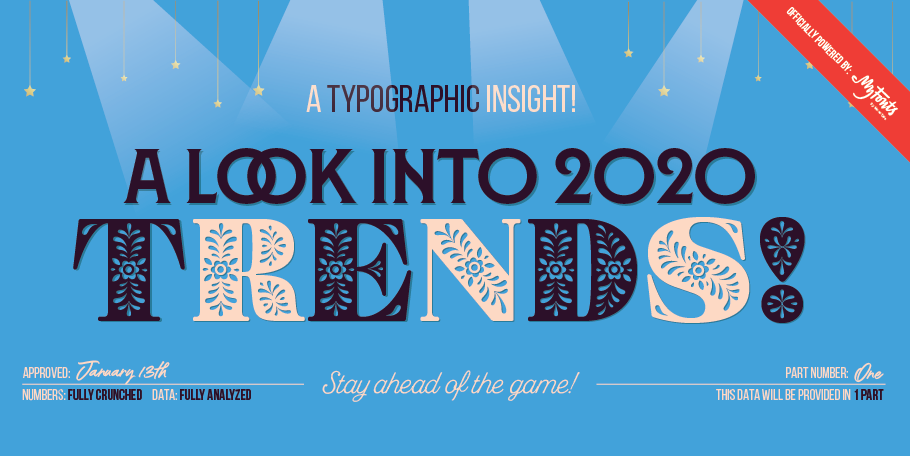
2020 Police Tendances pour les designers à utiliser cette année
" Des polices douces et des visages amicaux invitent les lecteurs à découvrir les annonces, les publications, les pages web et les jeux. "
L'utilisation de polices de caractères classiques dans vos projets présente peu de risques. Vous ne pouvez pas vous tromper avec Frutiger Suivante, Garamond ou Brandon Grotesque. Ces polices de caractères classiques sont comme une robe noire basique ou un blazer bleu marine.
Mais qu'en est-il si votre projet nécessite une typographie de dernière minute ? Que se passe-t-il si vous voulez une police qui s'inscrit dans une tendance typographique en plein essor - une police qui garantira que vos créations graphiques ou interactives sont fraîches, élégantes et branchées ? Lire la suite.
Même s'il semble que des centaines de nouvelles polices de caractères sortent chaque jour, les nouveaux designs police les plus en vogue se classent dans les catégories suivantes cinq catégories pour 2020:
• Sans géométrique
• Barres obliques et caractères alternatifs
• Polices et des visages amicaux
• Incrustée, gravée et délicieuse
• Square Sans
" Les swashs et les caractères alternatifs sont des éléments de personnalisation, tandis que les motifs incrustés, gravés et texturés se distinguent dans la foule ! "
Police Tendance n° 1 : Sans géométrique
Les polices géométriques sans fioritures sont à la mode depuis un certain temps, et ce pour de bonnes raisons. Elles s'expriment avec clarté et autorité. Beaucoup bénéficient également d'une large gamme de graisses et de proportions, ce qui les rend idéales pour tout ce qui concerne les mots-symboles, les marques, les titres et la signalétique. Le minimalisme est personnifié dans des designs tels que Gilroy, Biennale et Codec Pro. D'autres, comme Campton, sont adoucis par une subtile influence calligraphique. Cette influence calligraphique est encore plus forte dans des designs comme Noah et Proxima Nova.
Grâce à leurs grandes hauteurs de x, à leurs compteurs ouverts et à leurs formes de caractères simples, ces caractères permettent aux entreprises et aux produits d'exprimer leur marque de manière transparente partout où un public peut s'y intéresser, notamment sur les sites Web, dans les publicités, dans les messages d'entreprise, sur les emballages - et bien plus encore. Choisissez l'un de ces modèles et vous ajouterez à votre boîte à outils une police de caractères puissante, tendance et certainement classique.
• Biennale de Latinotype
• Campton de Rene Bieder
• Codec Pro de Zetafonts
• Gilroy de Radomir Tinkov
• Noah de Fontfabric
• Proxima Nova de Mark Simonson
Police Tendance n° 2 : les traits d'union et les caractères alternatifs
Les swashes et les caractères alternatifs sont synonymes de personnalisation et d'adaptation. Ils permettent de créer des titres et des bannières uniques et sont également parfaits pour les liens de navigation, les sous-titres et les emballages. Ce sont des choix idéaux pour les occasions spéciales qui exigent plus que des mots sur du papier. Certaines, comme Aire et Artis Sans, sont sophistiquées, avec des touches sensuelles et des fioritures. Le Desire a la proéminence d'une police à empattement classique et est rempli d'alternances, de ligatures, de swashs et même de mots d'accroche ! Gelato Fresco est aussi accueillant qu'une lettre à la main, tandis que VVDS Organum est un Didone majestueux à sept graisses avec une attitude enjouée. Ses nombreuses ligatures discrétionnaires et ses alternatives stylistiques permettent de créer facilement une typographie sur mesure.
• Aire de Lián Types
• Artis Sans de Wiescher Design
• Désir de Borges Lettering
• Gelato Fresco de Schizotype
• VVDS Organum de Vintage Voyage Design Supply
Police Tendance n° 3 : Polices et visages sympathiques
La douceur de polices et les visages sympathiques invitent les lecteurs à entrer dans les publicités, les publications, les pages web et les jeux. Certaines, comme ITC Souvenir, sont de délicieuses confiseries, tandis que d'autres, comme Supernett, ont une qualité naïve et charmante qui est tout simplement amicale. Les terminaisons arrondies de Duddy sont subtiles dans les poids légers, mais prennent de l'ampleur à mesure que les traits deviennent plus lourds. La famille Hornbill est le modèle parfait pour les personnes qui souhaitent une police de caractères conviviale et invitante, mais pas mignonne ou câline. Avec ses 64 dessins, cette famille est également suffisamment large pour s'adapter à pratiquement tous les projets. Recoleta charme les lecteurs avec un doux aspect Art nouveau.
• Duddy de Letritas
• Calao d'Eko Bimantara
• Recoleta à partir de Latinotype
• Souvenir ITC de ITC (une fonderie de monotypes)
• Supernett de FaceType
Police Tendance n° 4 : incrustés, gravés et délicieux
Les motifs incrustés, gravés et texturés se distinguent dans la foule ! Ils attirent l'attention. Ce sont d'excellents choix lorsque la perceptibilité est importante : lorsque vous voulez que les titres soient vus, que les emballages se distinguent sur une étagère, que les brochures soient prises en main et que les pages web soient accrochées. Ils ont tendance à être cultivés et chics, comme Ademo, Caslon Openface ou les jumeaux Joane "Deco" et "Engraved", mais ils peuvent aussi être rugueux et tumultueux, comme Shervington Engraved. Les lignes polices des familles Ambiguity et Trade Gothic Display "Layered" sont robustes et imposantes.
• Ademo de astype
• Caslon Openface de Bitstream (une fonderie de Monotype)
• Joane de la Fonderie W
• Shervington Gravé par Greater Albion Typefounders
• Ambiguity Inline de Monotype (A Monotype Foundry)
• Trade Gothic Inline
Police Tendance n° 5 : DIN Forget Square Sans
Les polices de caractères carrées sans empattement existent depuis le XIXe siècle, et l'on pourrait donc penser qu'elles ne sont plus à la mode. Pourtant, une nouvelle génération de polices de caractères sans empattement a commencé à faire son apparition dans tous les domaines, des vêtements à la signalisation. Pourquoi ? Parce qu'elles sont économes en espace, accessibles et prêtes à s'attaquer à des travaux de petite ou de grande envergure ! En outre, les formes carrées des caractères tirent le meilleur parti de l'espace disponible sur les petits et les grands écrans.
Agency Gothic CT redonne vie à la vénérable police de caractères métalliques des années 1930, réglée à la main, et élargit la famille en une suite pratique de dessins. BF Corpa Gothic Pro contient plus de mots que vous ne l'auriez cru possible dans le plus petit des espaces, tandis que les 85 dessins de la famille Refinery en font un véritable couteau suisse® de polices. Roag et Slow Tempo sont bien charpentés et confèrent aux titres et aux petits blocs de texte une atmosphère d'armement.
• Agency Gothic CT de CastleType
• BF Corpa Gothic Pro de Brass Polices
• Raffinerie de Kimmy Design
• Roag de The Northern Block Ltd
• Tempo lent du type Dharna